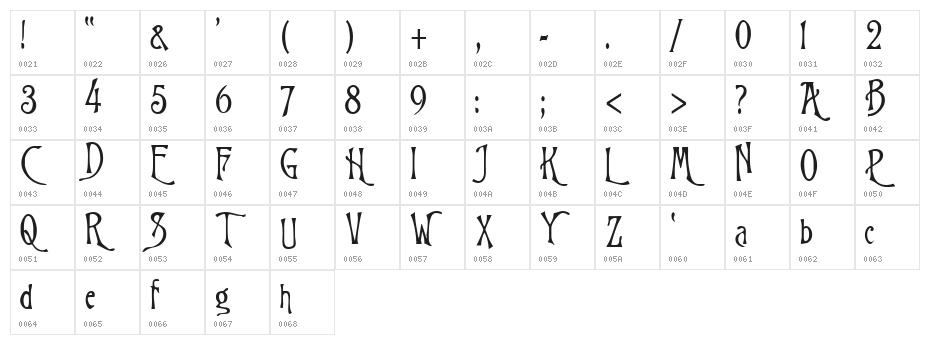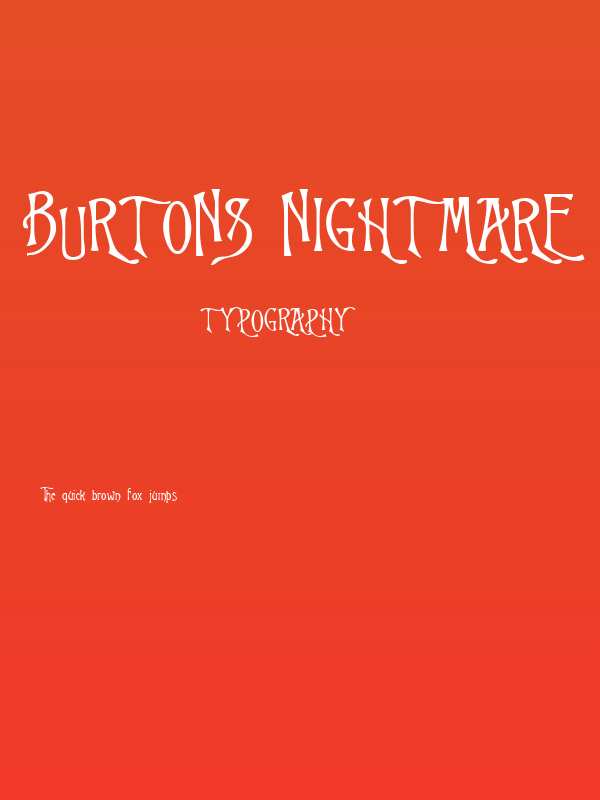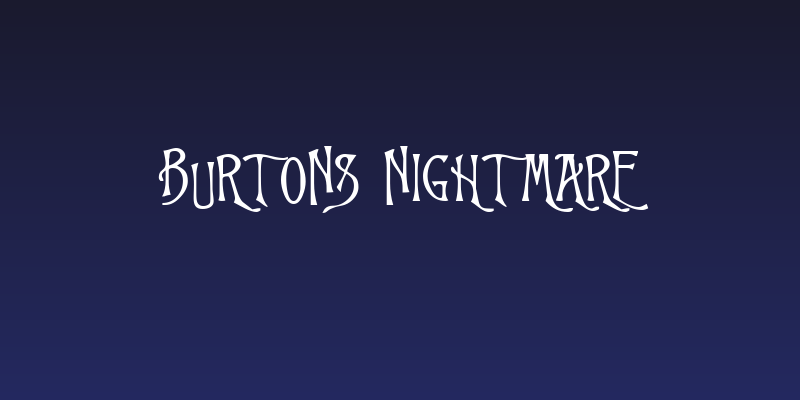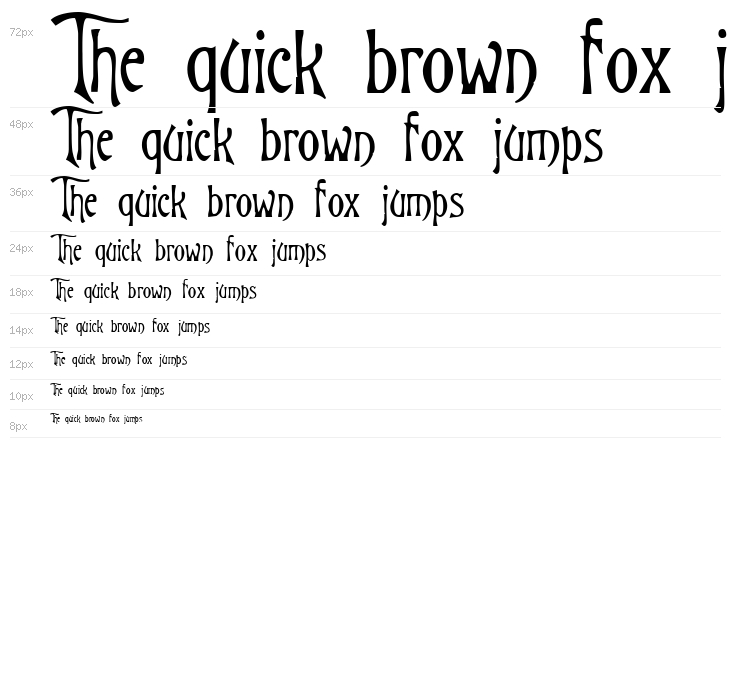
Burtons Nightmare Font
| Gesamtstil | Gothic, Whimsical, Fantastical |
| Anwendungsfall | Headlines, Posters, Themed Events |
| Vorgeschlagene Projekte | Ideal for Halloween-themed designs, fantasy book covers, movie posters, or any project needing a touch of the mysterious. |